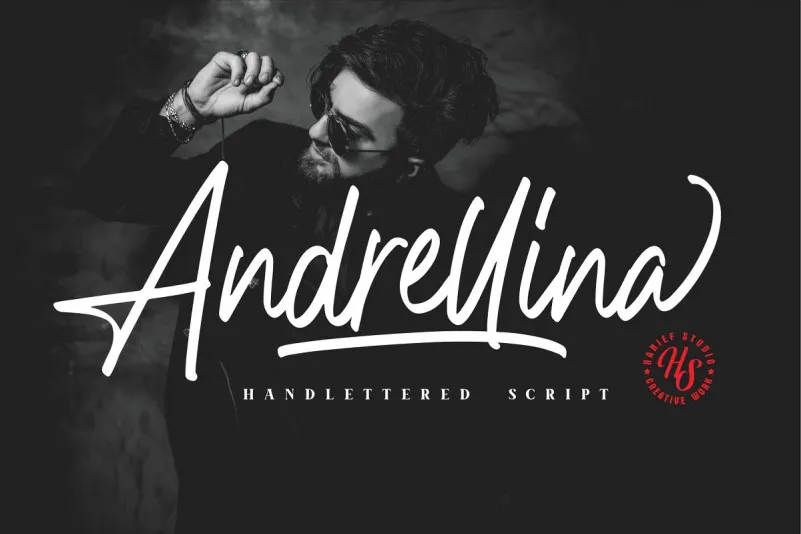
Andrellina Signature Font – Download Grátis
Olá, estamos orgulhosamente apresentando uma nova fonte escrita a mão script encantadora e bonita. Esta é uma fonte personalizada para assinaturas feitas à mão que traz texturas suaves e linhas elegantes. Com seu moderno estilo de letra, esta font será perfeita para diversos projetos como fotografia, marcação de água, citações, design web, cabeçalhos de blog, impressão de pôsteres, noivas, marcas, convites, cartões e notas de endereço. Cada uma das letras foi cuidadosamente criada para tornar seu texto ainda mais bonito. Se você está procurando por um estilo elegante que dê um toque pessoal à sua obra, Andrellina Font é a escolha certa. Experimente agora!